文字设计需要一定的技巧,能让文字呈现出良好的视觉效果。从设计师角度来说,设计技巧能让设计师快速掌握设计流程,更快、更好地设计出文字作品。对于消费者而言,使用过设计技巧的文字作品,在视觉上更加具有震撼力。
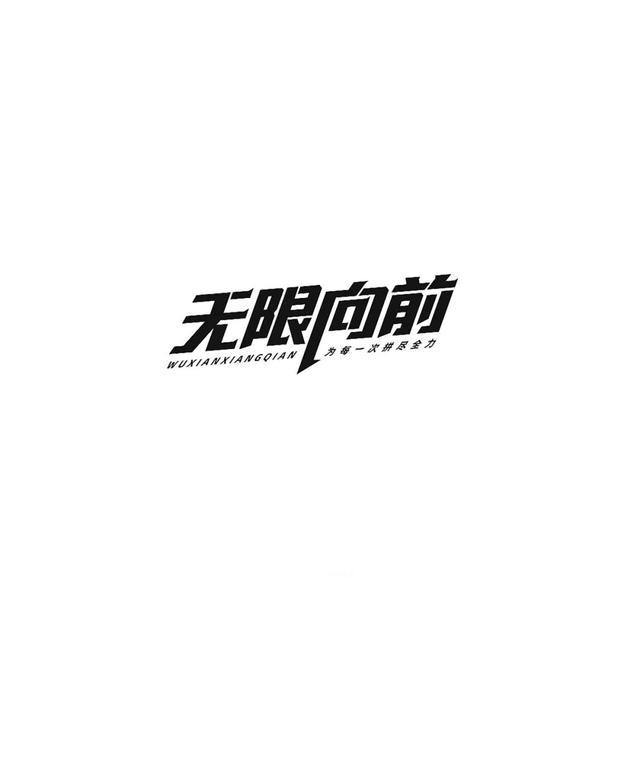
尖角法是将文字的圆角变成直尖卷尖、弯尖、斜尖等几种形式,这些尖角可以是竖向的,也可以是横向的。从视觉上来看,将原本浑厚的字体变成十分硬朗的字体,能表现出强有力的视觉感。
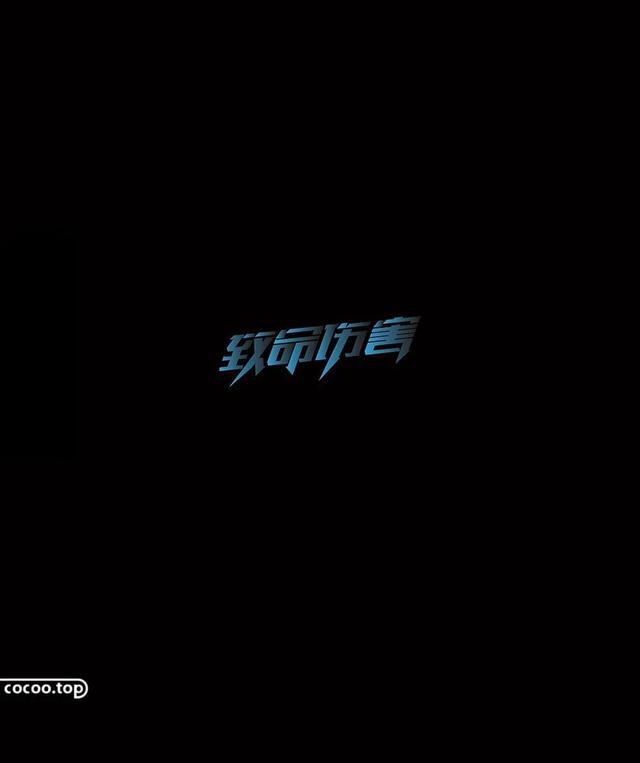
连笔法是通过相邻的字与字之间或者笔画之间自然的连接,来打破方块字之间的限制,形成活泼美观、字形连贯的文字形态。这种字体设计的巧妙之处在于能够让整个画面充满律动的美,连笔法讲究的是字体书写节奏的流畅。
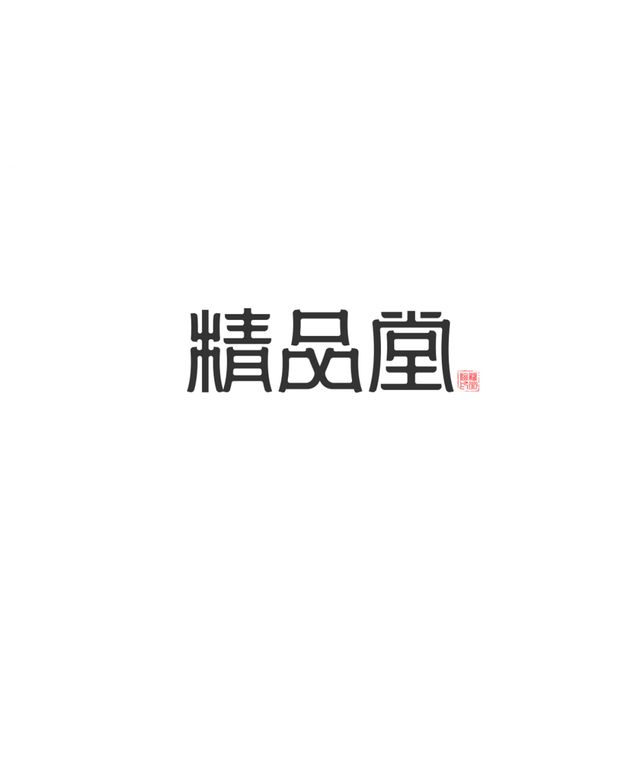
设计时应选择可连接部位或共同的笔画,根据文字的内容和特点进行构思笔画可长可短,字形可大可小,使字体产生均衡与对称、对比与统一的和谐感。
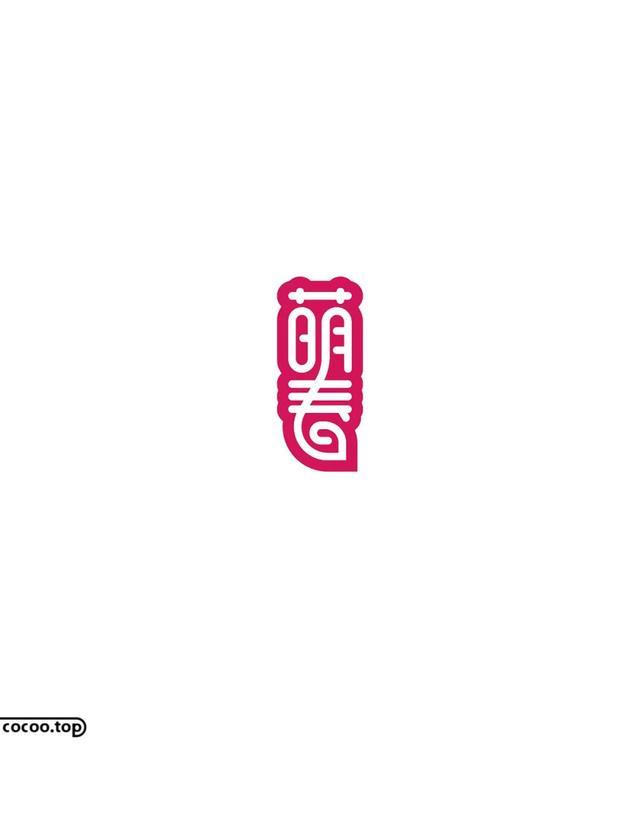
粗细法是将竖线或者横线转换成其他类型的线条,将笔画简化的一种设计手法。精细法能够给人一种重力分化的视觉感受,字体较粗的一方显得重,字体较细的一方显得轻。
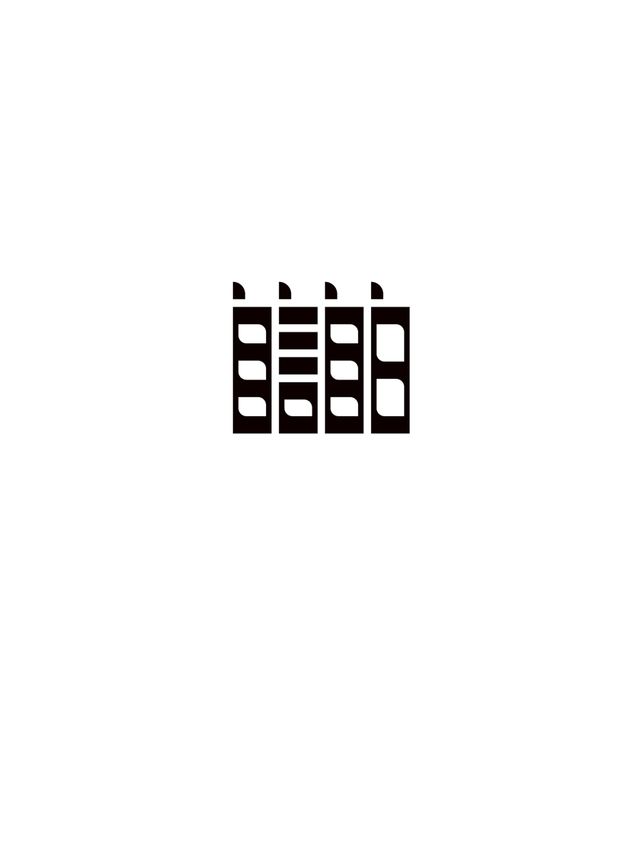
断笔法是将文字闭合包围的地方适当地开口,或者将某一处断开一部分,使前后笔画之间不再紧密相连。这种设计方式可以使文字具有设计感与现代感。
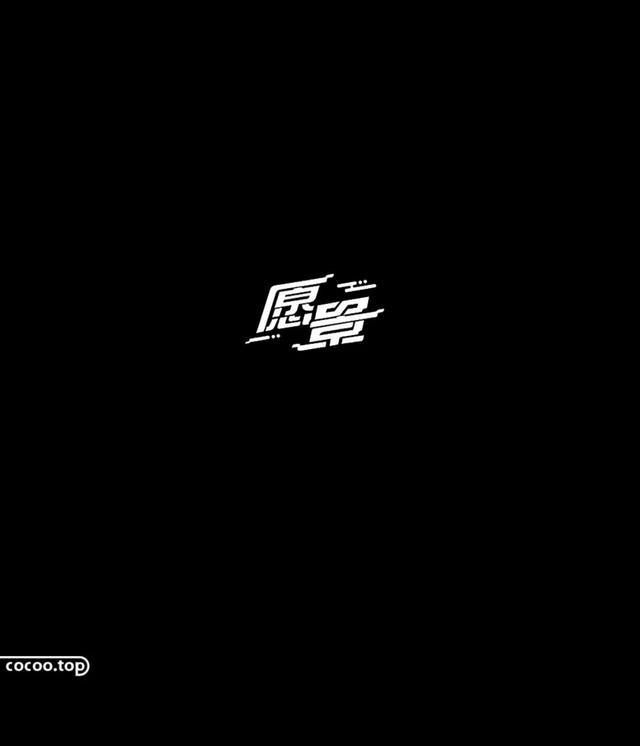
断笔法还可以将文字的不同部位做些颜色与形式上的变化,从而达到意想不到的效果。对文字的笔画采取错移、分解、剪切等方式,使其呈现出缺口,产生断裂、破碎、粗犷等感觉,能带来极为震撼的视觉感受。
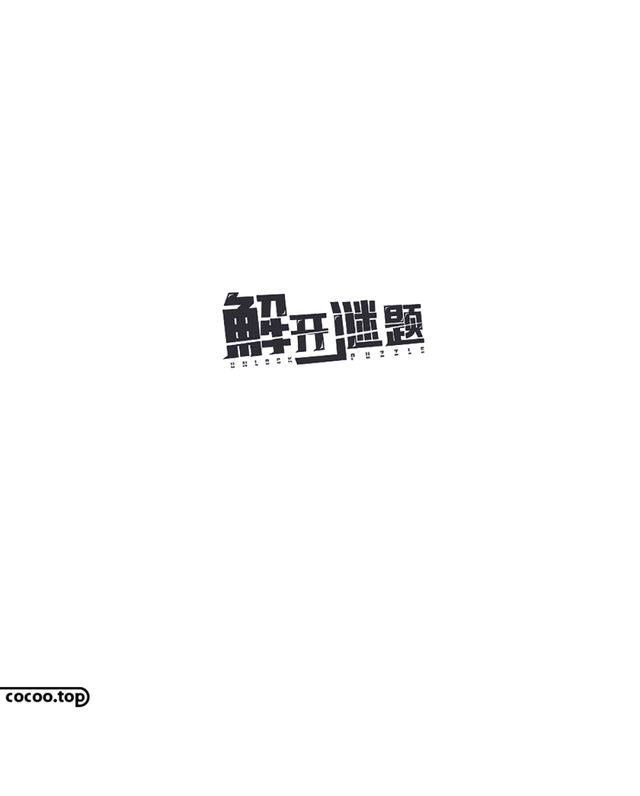
空心法是利用线条勾勒出文字的外部轮廓,将字体的中间进行留白处理。在设计的过程中,过粗的字体轮廓会产生相合或重叠的现象。
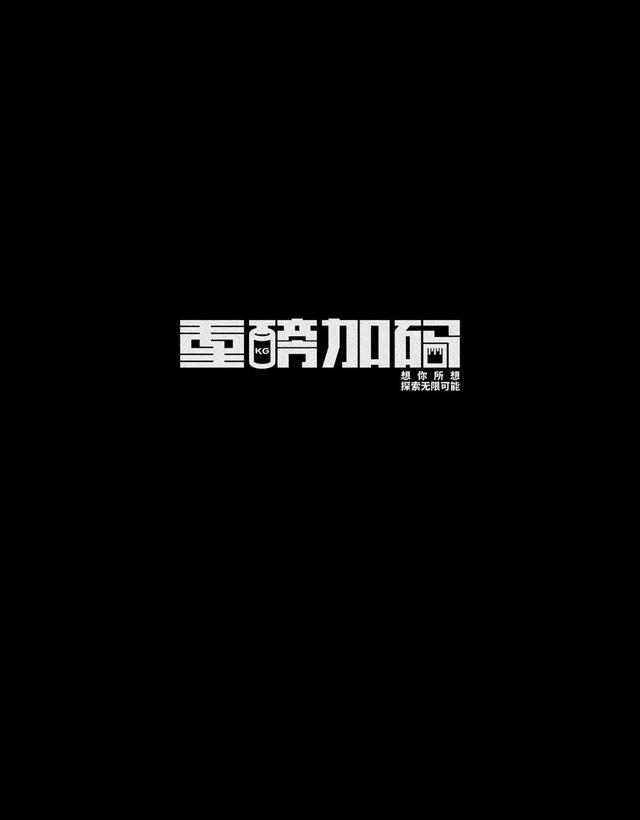
在大多数情况下,对于字体笔画的形状设计,主要是根据文字所应用的领域及要表达的主题,有针对性地来改变字体的笔画形状,符合宣传的对象与环境,创作出相符的设计作品,起到更好的传播作用。
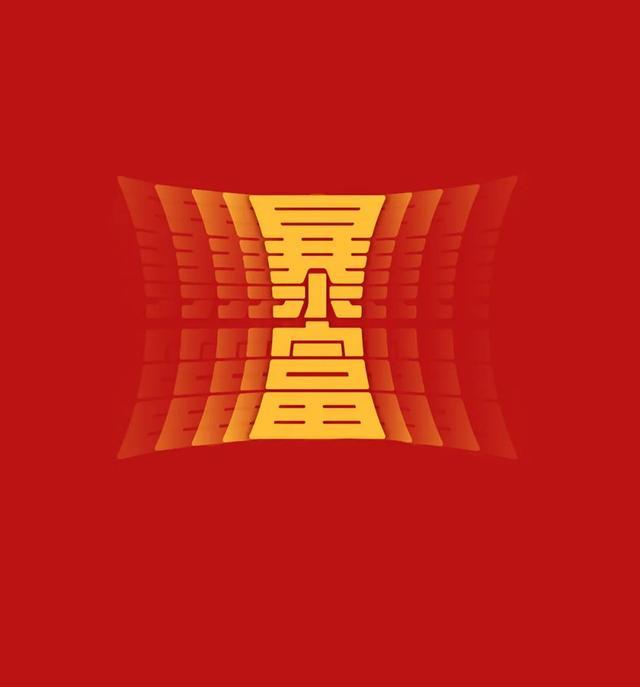
利用字体基本的笔画构成,按照字体的实际内容与含义将笔画变形,使之呈现出夸张、独特的形状,以此达到突出主题的目的。
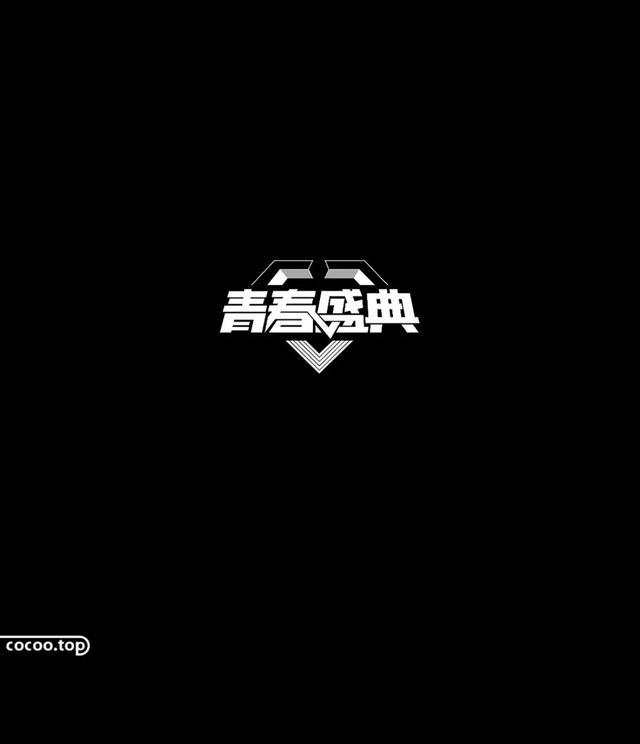
①错位。错位设计是将整齐的字体错开排列制造出一种错落有致又富有韵律感的艺术效果。这种排列方式让原本规则的文字富有变化。
②伸缩。伸缩设计是以最为简单的伸缩方式进行文字处理,以拉大、缩小、压缩等方式改变文字外形,虽然在设计上没有做较大的改变,但是这一设计形式却赋予了文字新的生命,提升文字的档次。
③描边。描边通俗来讲就是在文字的边缘加上边框,在字体上描绘出新层面。这种设计手法能够突出文字,强化文字边缘,让字体显得敦实厚重。
字体笔画的共用,顾名思义就是指两个或两个以上的多个字体共同采用同笔画构成文字形态,将不同的字体通过重合、相接的同一笔画联系在一起,形成具有独特风格的新型复合字体,展现出字体设计的多样性。
对于字体而言,笔画的共用既有美观大方的简洁特征,又能打造出具有独特个性的字体形态,使作品产生美好的艺术画面,进而达到宣传文字含义与设计精神的作用。总之,字体笔画的设计与变化,是为了赋予字体更强的感染力,使其积极有效地吸引人们的关注。
字体装饰设计是在保持文字整体不变的情况下,将字体的笔画做一定的装饰性设计,在保障文字信息传达功能的前提下,提升文字版面的形式美感。
设计领域中字体笔画的装饰设计,不仅能让文字摆脱单一的记录传达功能,还能在这些简单的基本特性上体现设计师的艺术造诣,增强字体的表现力。通过对笔画的修饰,使字体呈现出优雅、流畅的节奏美感。
对于字体笔画的装饰设计,不仅要注意保持文字的可读性,使内容的表达能够简洁清楚,同时更要注意表现出字体设计的艺术化特征,给人们留下深刻的印象体现视觉形象的新型审美观念,带来美好的视觉享受。